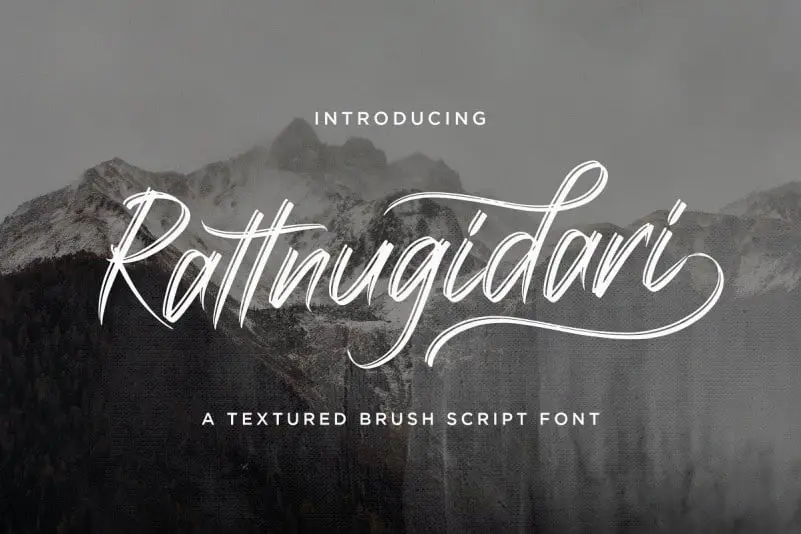
Rattnugidari Brush Font – Download Grátis
Rattnugidari Brush Font é uma fonte de script que traz a autenticidade das letras escritas à mão, com traços claros e robustos para criar texturas intrigantes. Esta fonte foi criada pela StringLabs e está disponível no catálogo do 99designs como parte da categoria de fuentes de texto script. Rattnugidari Brush é uma fonte de texto com textura, fresca e autêntica que complementa perfeitamente designs que valorizam texturas e formas amigáveis. Perfeita para criações visuais como logotipos, marcas, panfletos ou qualquer outro projeto que desejamos dar um toque de originalidade com textura e força. Rattnugidari Brush traz uma sensação de modernidade leve e contemporânea, sem perder a elegância do design tradicional. Com seu foco em letrar bem tanto em headlines quanto em seções de texto mais extensas, é claro que você vai adorar usar esta fonte no seu próximo projeto gráfico.